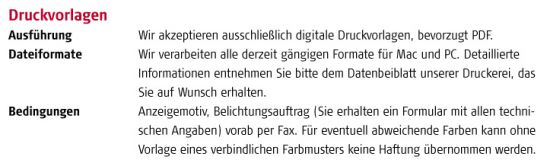
Schrift mit offenem G gesucht!
ich suche den Namen folgender Schrift. Markant ist beispielsweise das kleine g.
Jetzt suche ich noch diese Schrift hier:
Ich habe jetzt noch eine ähnliche Schrift gefunden, die ich ein bissl schöner finde.
Könnt ihr mir auch bei dieser mit dem Namen helfen?
Es handelt sich um den Schriftzug "Skilsaw".
(wenn ein schärferes Bild gebraucht wird, bitte Info)